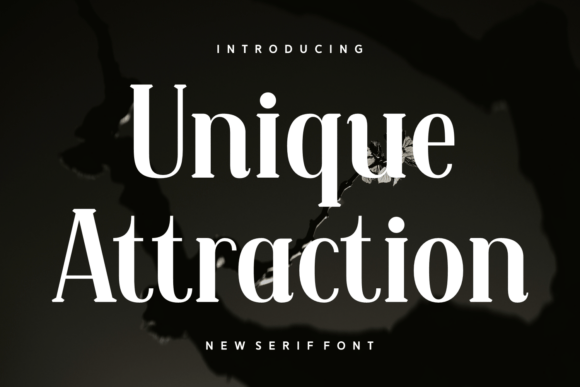
Unique Attraction
適切なデザイン要素を見つけるのは難しい場合がありますが、Unique Attractionは作品を即座に引き立てる優れたコレクションを提供します。
POD(オンデマンド印刷)製品、結婚式の招待状、またはソーシャルメディアのグラフィックを作成している場合でも、Unique Attractionは理想的です。